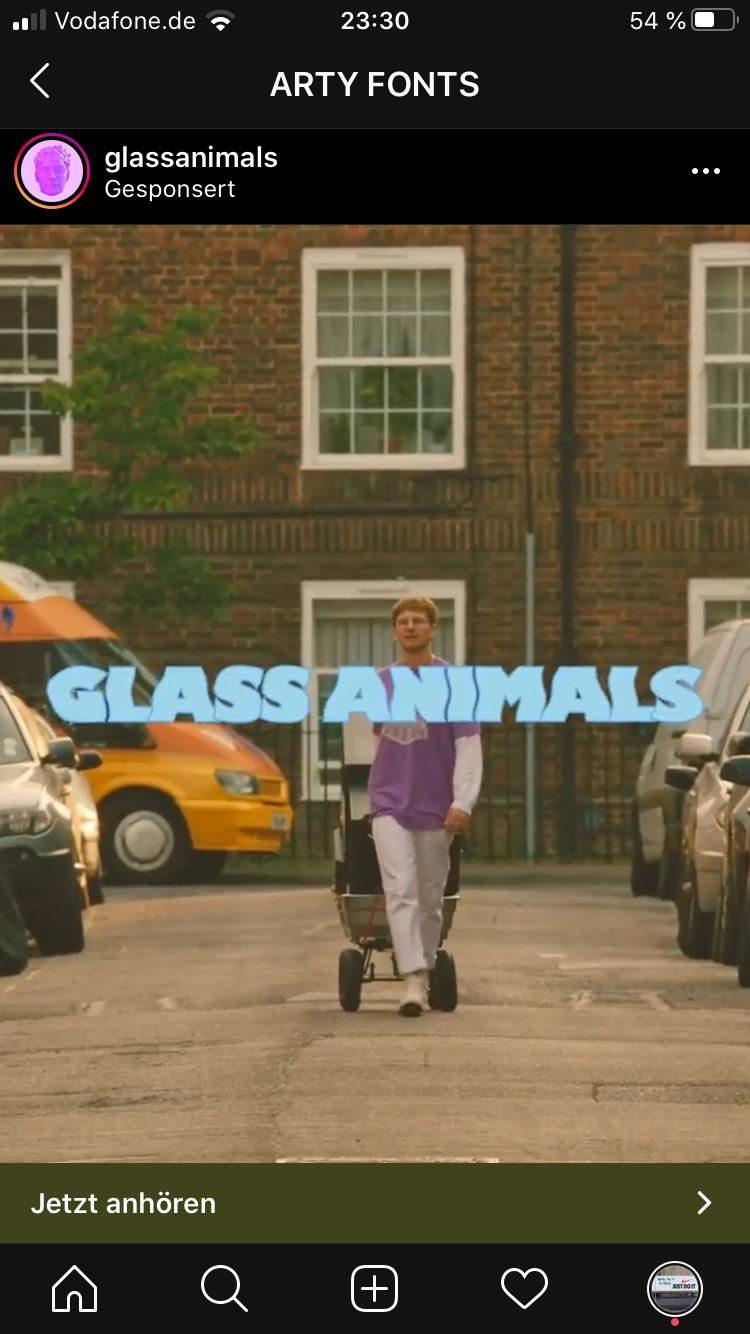
Suche die Schriftart dieses Instagram-Posts! (glassanimals)
Hi, ich suche die Schriftart des angehängten Bildes. Im Video ist ein leicht welliger Effekt auf dem Text, weshalb die Schrift dementsprechend aussieht. Mir geht es jedoch erstmal nur um die Schriftart. Bin über jede Hilfe dankbar!